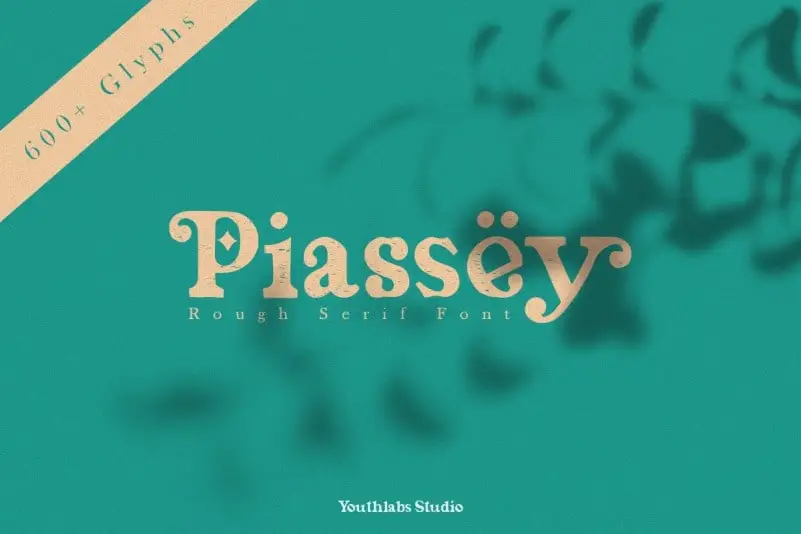
Piassey Rough Serif Font – Fonte Grátis
Piassey Rough Serif Font
A Piassey Rough Serif Font foi criada para atender às necessidades dos designers que buscam texturas naturais nos projetos. Com seu design grotesco e textura suave, esta fonte é uma escolha perfeita para tipografia de destaque, como em anúncios, logotipos, convites, material de estação, panfletas, etiquetas e bandejas. A Piassey oferece uma variedade significativa de caracteres alternativos e suporte multilíngue, tornando-a ainda mais versátil e adaptável a diferentes necessidades de design. Ideal para projetos que exigem um toque natural em seus layouts visuais, essa fonte é um recurso valioso para designers atentos à qualidade e consistência do seu trabalho.